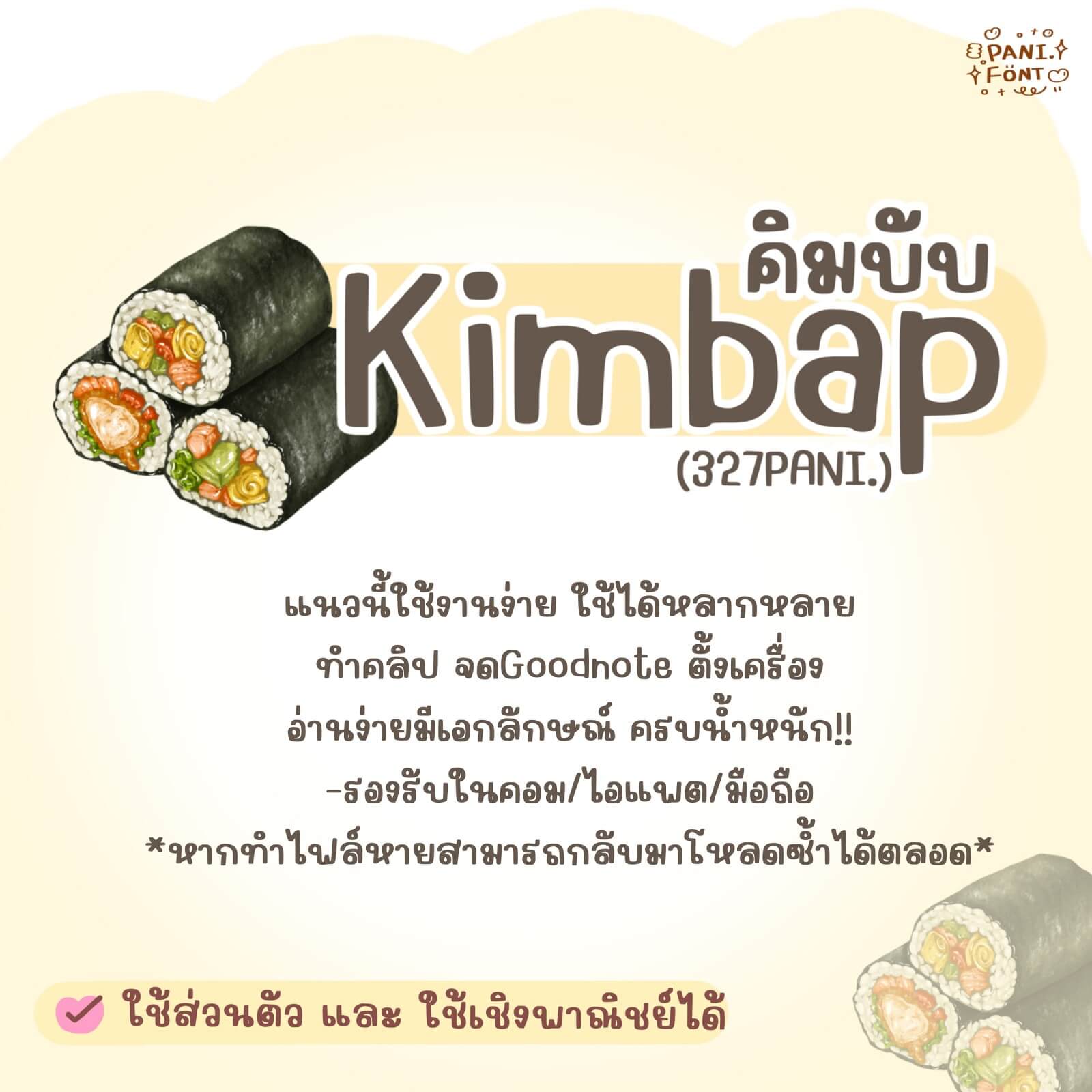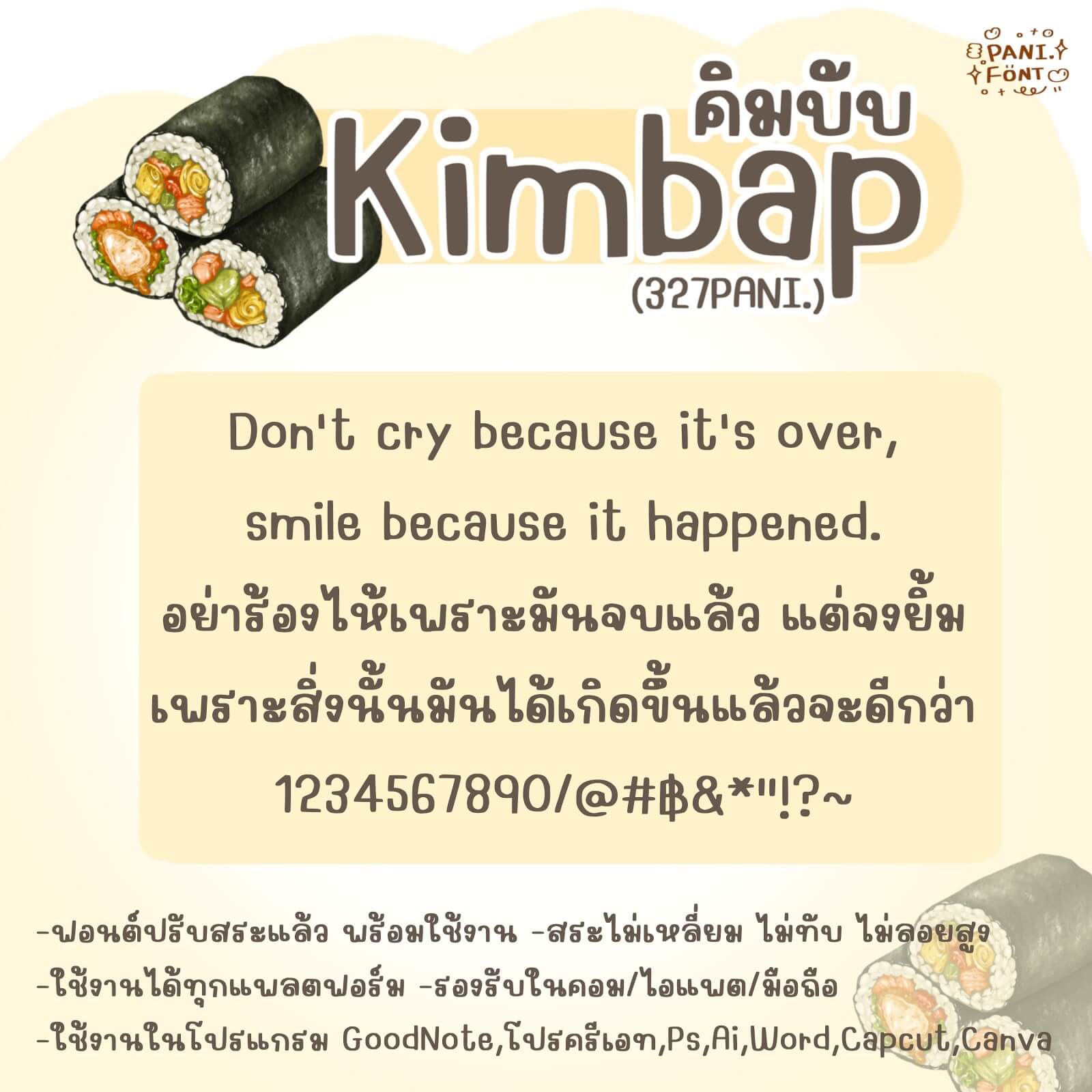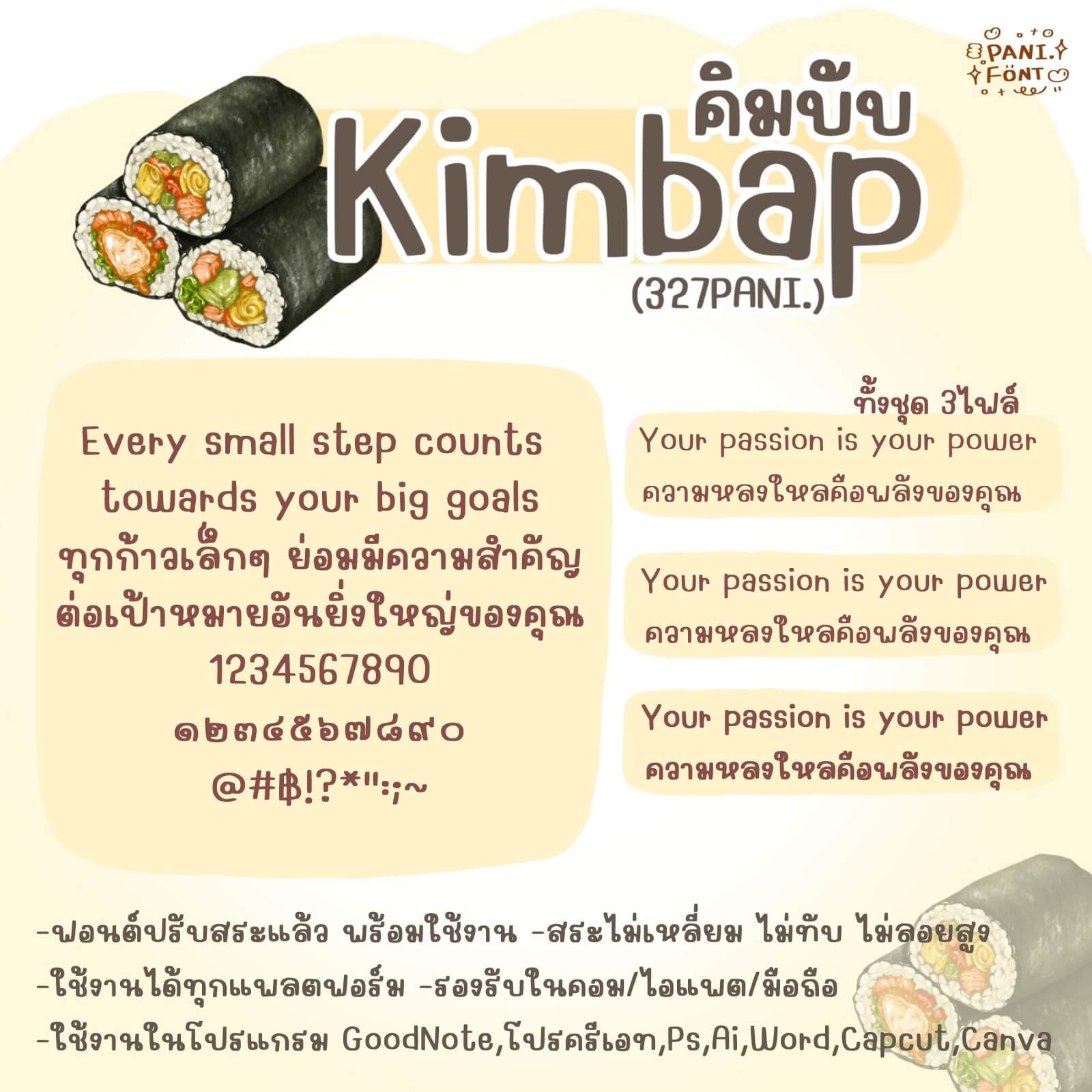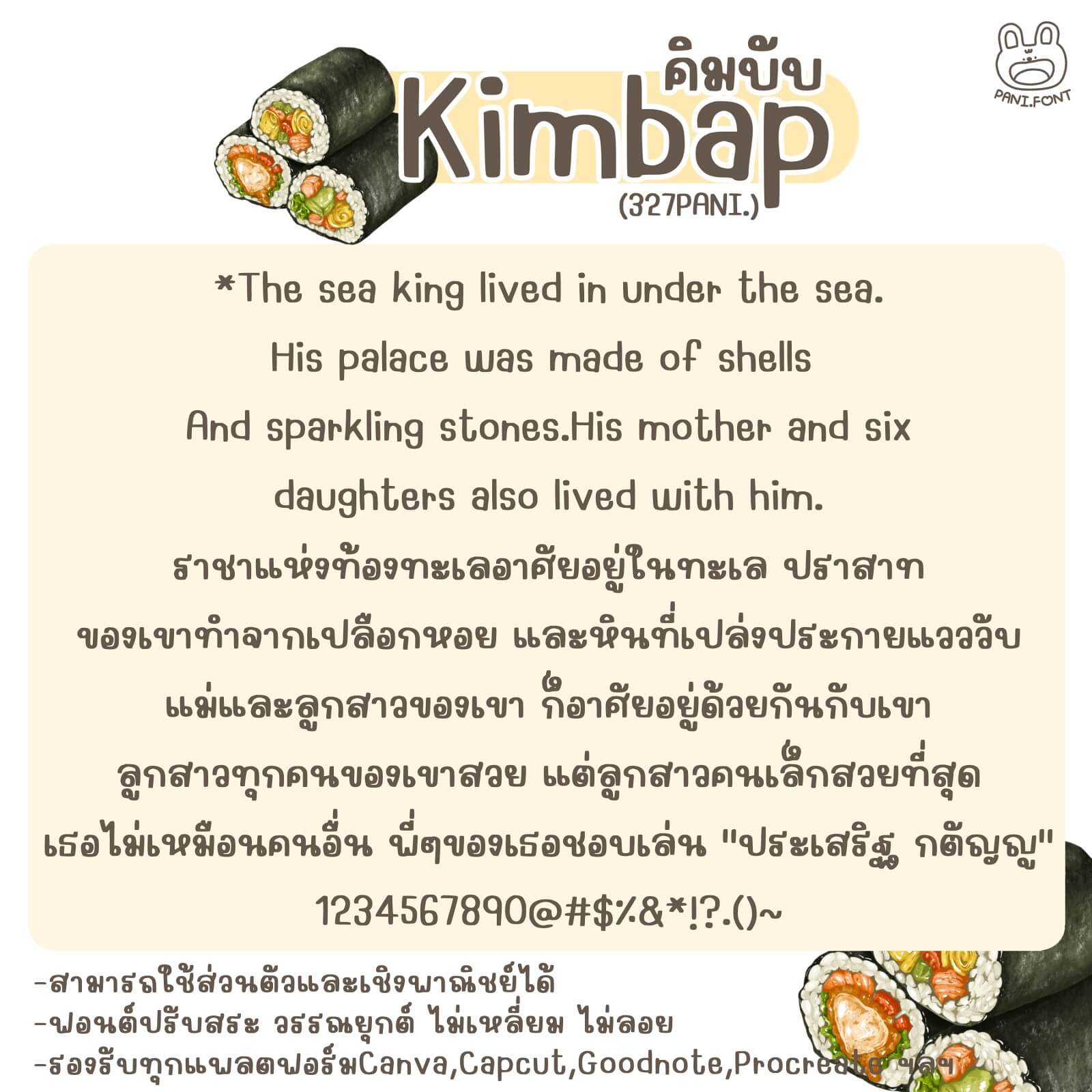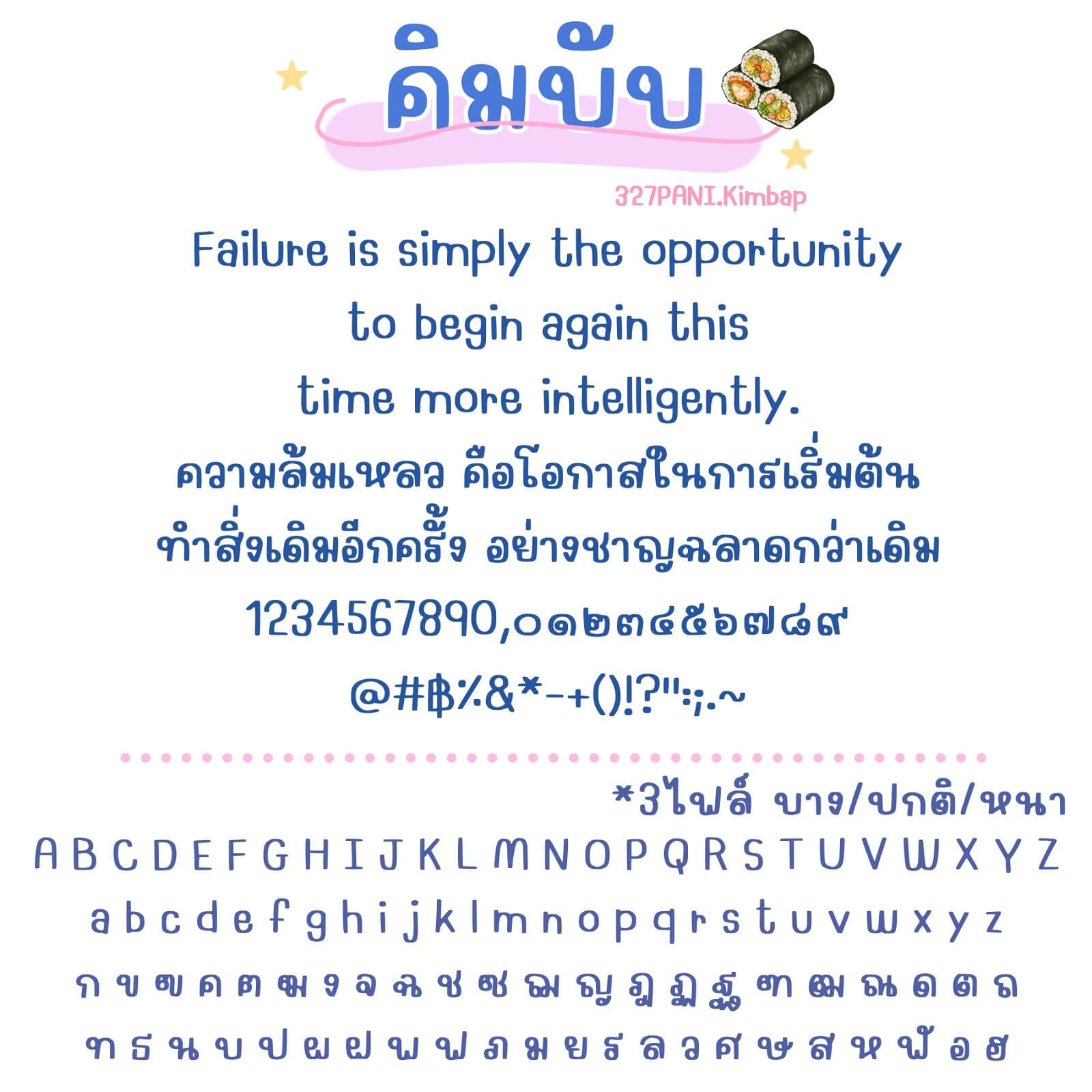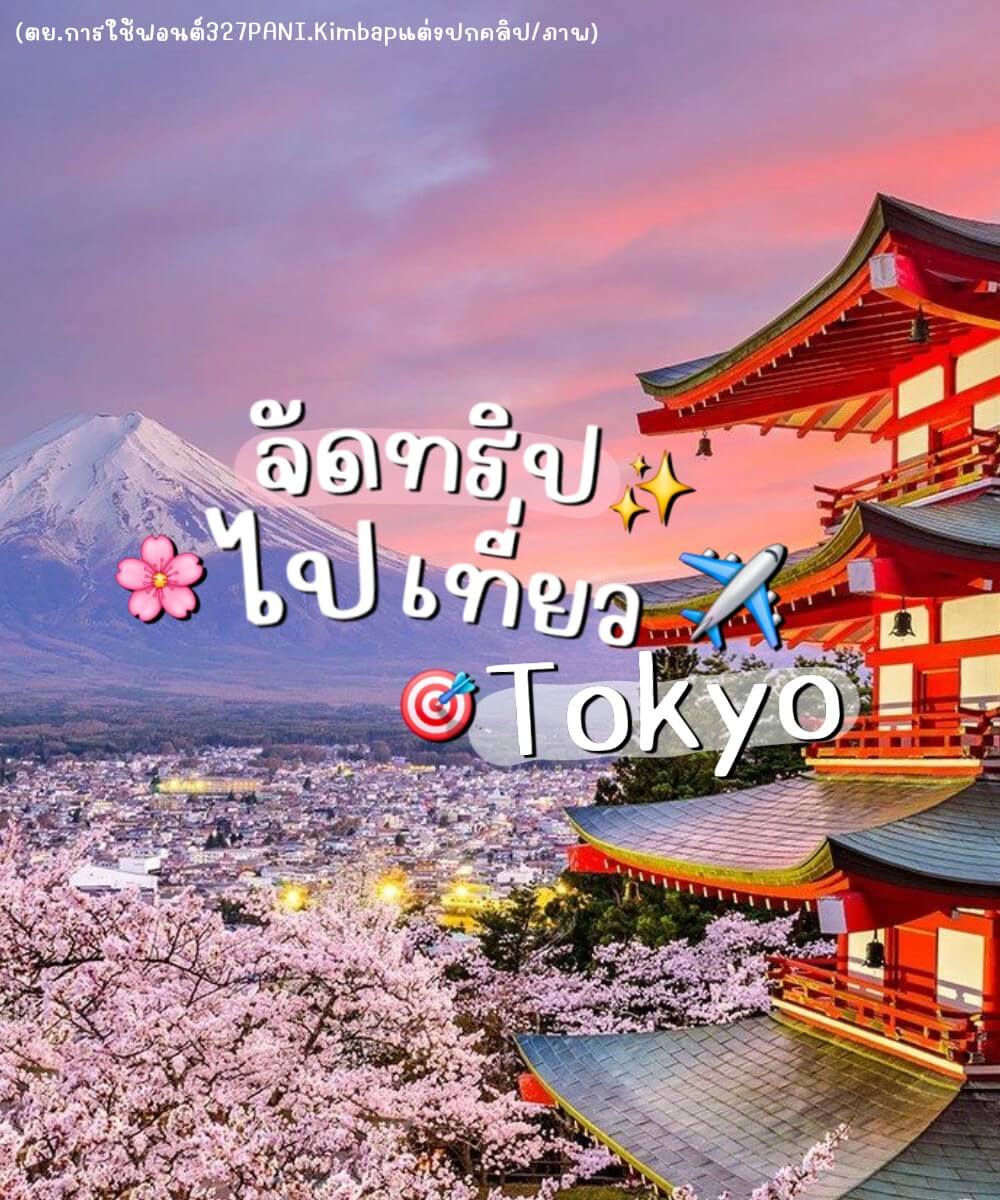
ฟอนต์ 327PANI.คิมบับ – โหลดทดลองใช้ฟรีตัว Demo แนวนี้ใช้งานง่าย ใช้ได้หลากหลาย ทำคลิป จด Goodnote ตั้งเป็นฟอนต์เครื่อง อ่านง่ายมีเอกลักษณ์ ครบน้ำหนัก!!
327PANI.คิมบับ (327PANIKimbap)